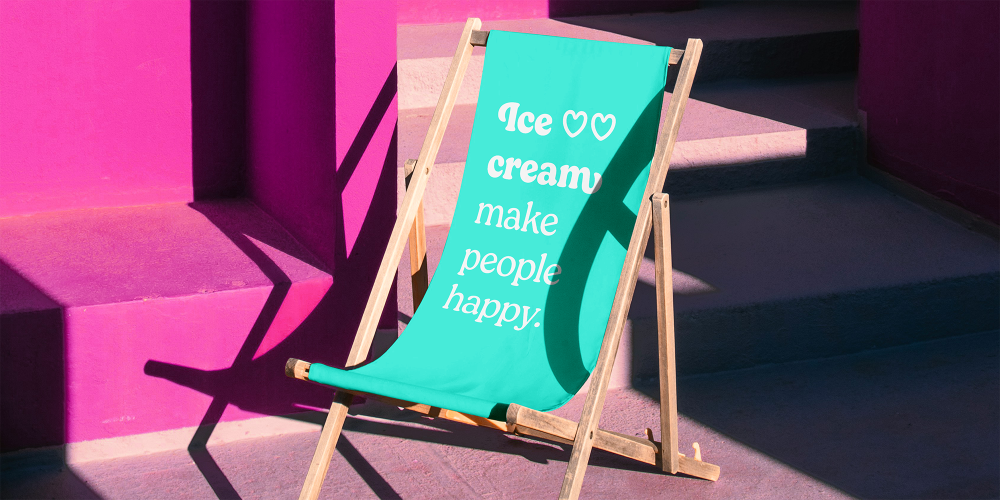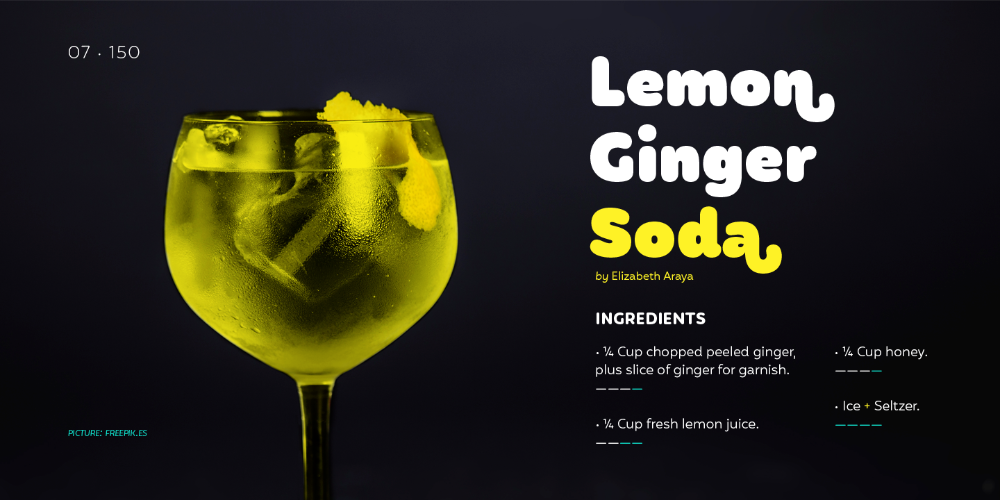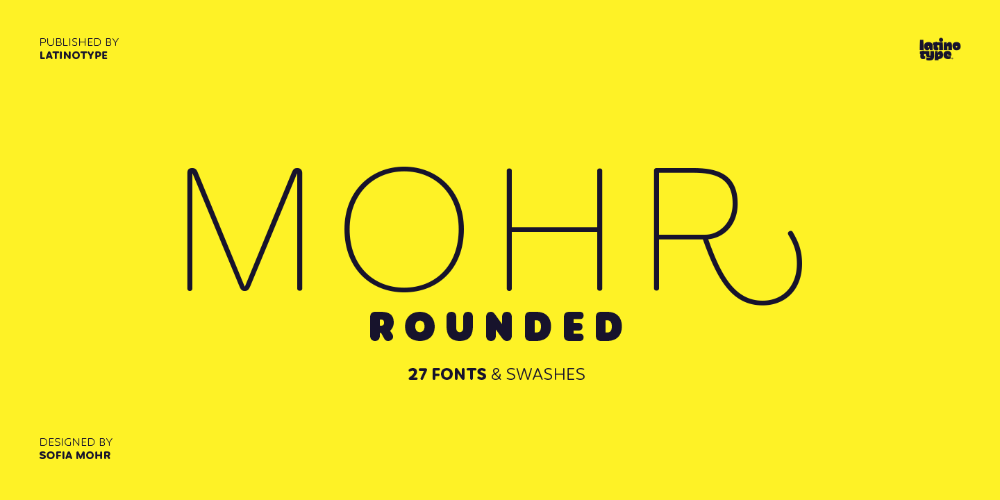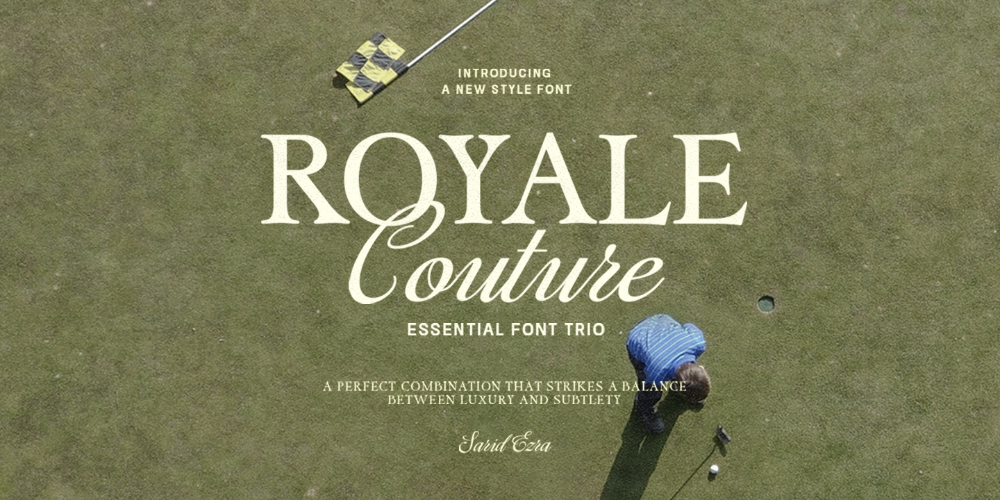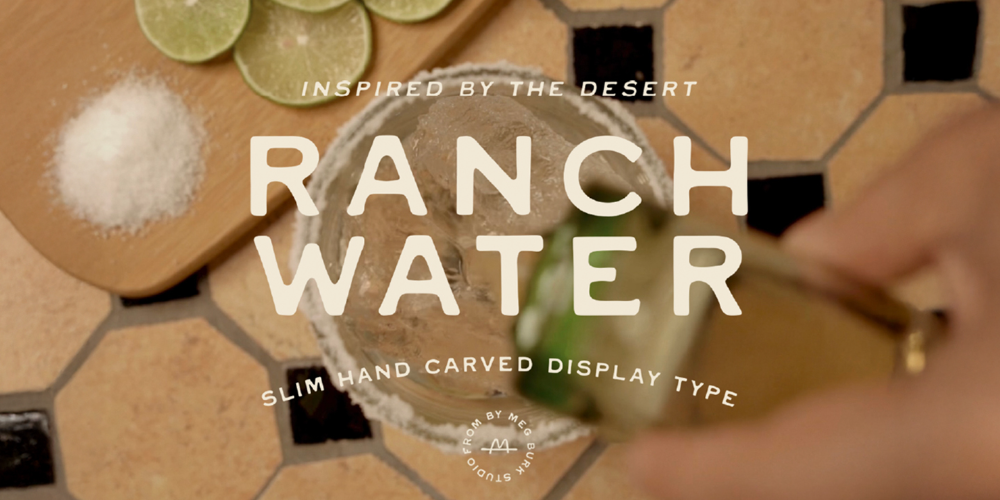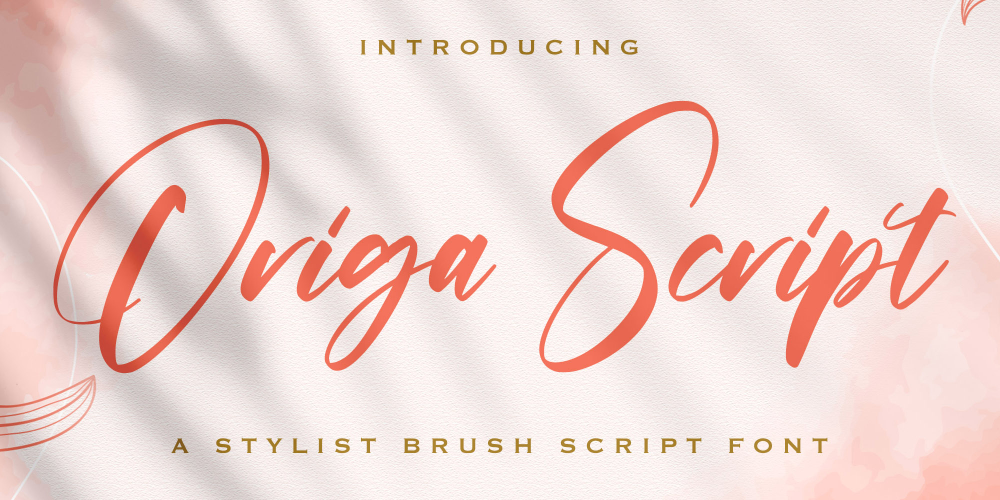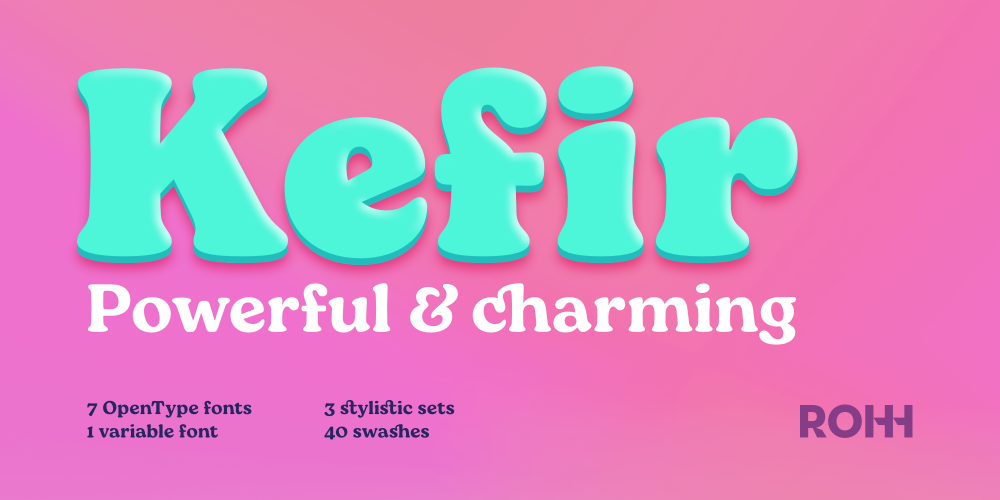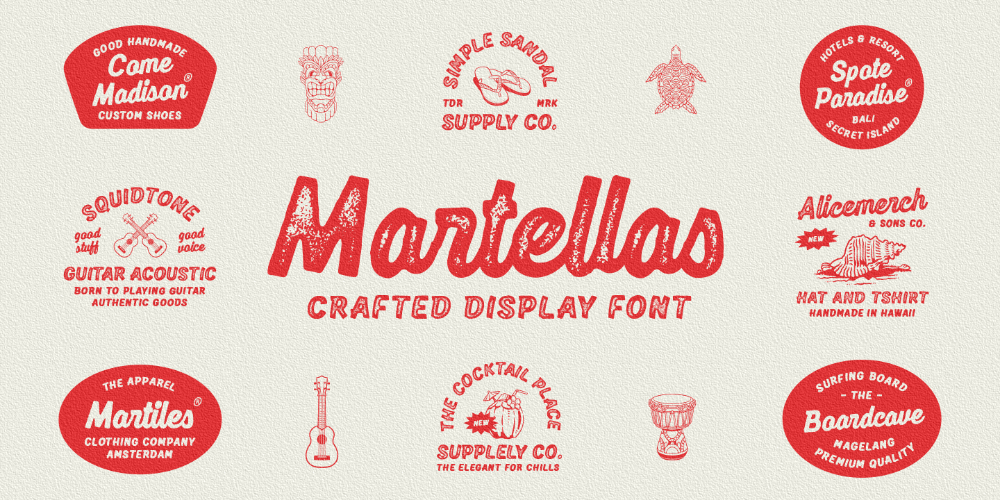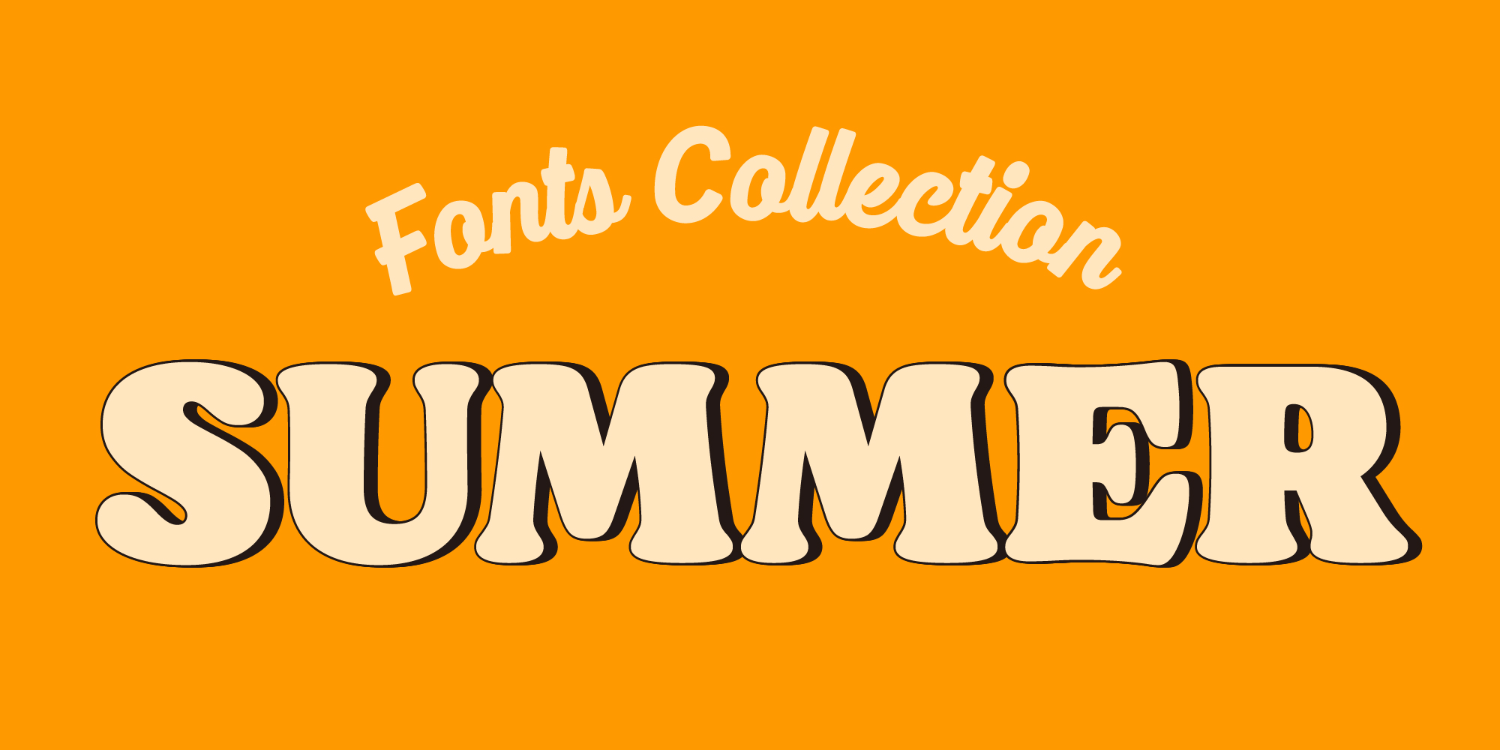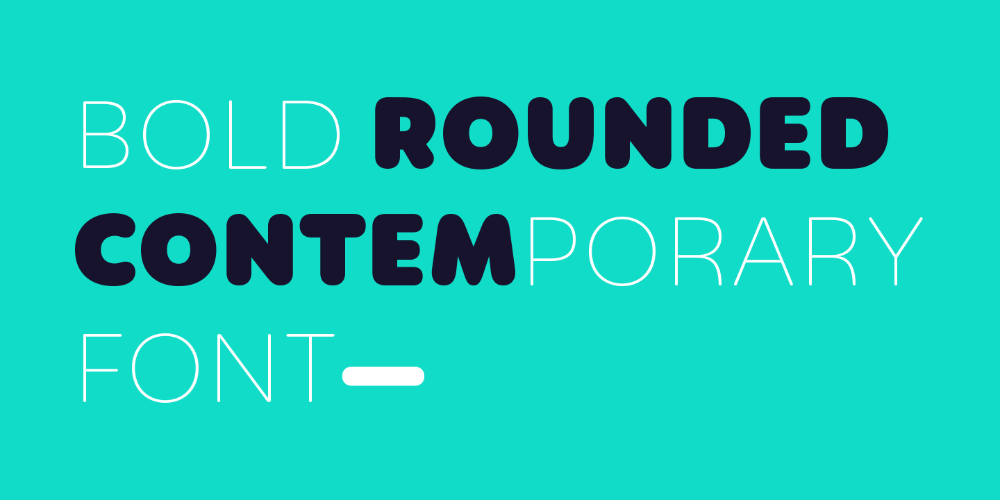
夏至到来,蝉鸣渐起,关于夏天的色彩与节奏也变得格外鲜明。无论是都市夏夜的片刻清凉,还是海边假日的明媚阳光,在这一季的设计中,总能找到更多夏日的痕迹。而字体,正是唤起这些感官记忆的重要载体。
本期,我们精心挑选 10 款夏日氛围感字体,或轻盈清爽,或热烈活力,不妨一同开启这趟视觉旅程,让创意灵感随字体流动。
1|Mohr Rounded
Foundry:Latinotype
Mohr Rounded 是 Mohr 字体的新版本,以更圆润柔和的笔画末端,营造出自然、温暖又富有亲和力的视觉感受。就像夏日微风中轻轻晃动的标牌、饮品包装上的圆润字样,这款字体散发着轻松而友好的气息。
Mohr Rounded 字族提供常规、替代与斜体三种风格,每种均涵盖从极细到特粗的 9 款字重,共 27 种样式,适配从正文到标题的多种排版需求。其大写与小写字母中还内置了装饰性笔画,为品牌及包装设计等带来更多元的夏日创意表达。
2|Kefir
Foundry:ROHH
Kefir 就像那个总能带来轻松气氛的夏日好友,自在有趣,令人一见倾心。它圆润亲切的字形与灵动俏皮的装饰笔画,为设计注入了令人愉悦的温度,无论是打造吸睛的饮品标签、杂志封面,还是品牌广告与包装设计,Kefir 都能带来一抹清新又富有个性的夏日风情。
Kefir 提供灵活可调的可变字体格式,以及两套风格化字形,可自由切换笔画走势,帮助设计师打造更具表现力的视觉语言。超过 650 个复古风格字形,搭配活泼的花笔(Swash)装饰,支持扩展拉丁字符,轻松驾驭多语种排版,特别适合展现夏季的轻盈、欢乐与多元。
3|Summer Wave
Foundry:Qweera Studio
如海风拂面,Summer Wave 是一款充满夏日气息的手写字体,拥有自然流畅的笔触、优雅的连笔与个性化的替代字形,展现出复古与现代并存的迷人风格。
它尤其适合用于品牌设计、杂志排版、社交媒体与印刷应用,为作品带来轻盈而灵动的手写质感。
4|Martellas
Foundry:Edignwn Type
Martellas 的设计灵感源于夏威夷风情元素,是一组专为品牌标识与标题应用打造的字体家族,包含手写体与无衬线体,每种风格均提供 Regular、Rounded、Rough 与 Stamp 四款样式,满足不同质感需求,搭配出多元创意。
Martellas 融合了复古与现代的视觉语言,适用于徽章、海报、包装、T 恤等多种应用场景,尤为适合打造具有手工感与个性的品牌形象。套装额外附赠一组夏威夷主题插画素材,更添热带度假风味。
5|Hanley Pro
Foundry:District 62 Studio
Hanley 是一组从手写字体出发、逐步延伸而成的复古展示字体家族。设计团队在品牌创作中反复寻找一款「有年代感但不过于老成、略有休闲但不运动风」的手写体,最终决定自己动手打造,从此开启了 Hanley 的诞生故事。
除了最初的手写字体,Hanley 还包含了窄高体、无衬线体标题、大小写混排的木刻感字体,以及一整组复古装饰元素。整体风格温润自然、略带手工痕迹,在复古与现代之间取得巧妙平衡。
如果你正在构思一款带有手工感的品牌标志、怀旧风格的包装或夏日市集的宣传物料,Hanley 都能提供灵活而统一的字体搭配方案,让设计更具故事感与亲和力。
6|Cruel Summer
Foundry:Sarid Ezra
Cruel Summer 是一款充满张力的手写风格大写字体,以干刷笔触绘制而成,粗犷不羁,质感十足。字形保留了笔触的天然纹理,带来强烈的手工感与街头气息,一气呵成,伴有随性之美。
这款字体非常适合用于标语、海报标题、菜单或需要强调个性的品牌设计中,尤其是你需要营造手写质感和类似粉笔的笔触时,这款字体会是不错的选择。
7|Royale Couture
Foundry:Sarid Ezra
Royale Couture 是一组风格协调的多字体组合,包含粗衬线体、经典无衬线体与优雅手写体三种风格,一套搞定字型搭配。
从浪漫柔和到率性现代,Royale Couture 就像一套为夏日场合量身定制的组合,清爽休闲又不失浓郁复古,轻松应对多种视觉风格与场景需求。
8|Ranch Water
Foundry:By Meg Burk
Ranch Water 是一款兼具粗犷与精致的字体作品,灵感源自美国西部的木刻路牌,是人气字体 Cowboy 的进化版。相比前作,它线条更纤细、造型更平衡,新增的小写字母也让排版更具灵活性。
这款字体自带阳光下公路旅店的粗犷感,适合用于乡村风格、复古包装、饮品品牌等需要手工质感的设计。无论你要打造一款如同「西部冰饮」般清爽的夏日视觉,或是传递自然原始的品牌个性,Ranch Water 都是值得尝试的选择。
9|Origa Script
Foundry:Stringlabs Creative Studio
Origa Script 是一款优雅的手写字体,模拟墨水在纸上流动的感觉,字形圆润流畅,节奏自然,犹如仲夏午后的轻风拂过,带来亲切而富有格调的视觉体验。
这款字体兼具艺术感与清晰度,适用于品牌标识、社交媒体、包装设计等需要传递个性与温度的场景。
10|Angika Jaya
Foundry:Edignwn Type
Angika Jaya 是一款精致、优雅且富有流动感的手写字体,笔画之间留有恰到好处的呼吸感,仿佛阳光下缓缓飘动的丝带,为设计注入一份轻盈柔美的气质。
其匀称而富有节奏的字符结构,适用于多种创意场景,能够自然融入并赋予作品灵动意趣,焕发手写的真挚温度。
"title": "一字入夏:精选 10 款夏季氛围感字体特辑"